第158回芥川賞と直木賞の選考会が1月16日に東京・中央区の料亭で開かれで開かれ、芥川賞は若竹千佐子氏「おらおらでひとりいぐも」と石井遊佳氏「百年泥」の両名が受賞し、直木賞は門井慶喜氏の作品「銀河鉄道の父」が受賞した。
金を落とすのは金も時間もある老人ということで文学界・出版界に訪れる超高齢化の波
女性の年齢を書くのも野暮と承知の上、石井遊佳氏は54歳、至ってはとか書くのは気が引けるし過去には黒田夏子氏が75歳9か月での受賞という最高齢受賞を記録しているのは承知で書くが、若竹千佐子氏に至っては63歳という年齢での芥川賞受賞となった。
こうした状況をみるに、もちろん作品自体が素晴らしいという事は一旦隅においておいて、文学・出版界にはやはり超高齢化の波が押し寄せていると穿った見方で邪推してしまった。
2017年のベストセラー第1位が「九十歳。何がめでたい」であった事も後押ししたんではなかろうか。著者である直木賞作家・佐藤愛子氏も1923年11月5日の94歳。やっぱりこんな事を書くと怒られるかもしれないが老人によるエッセイだ。
老人によるエッセイが老人のために書かれたとまではいわないが、若者の活字離れが叫ばれて若者が本ではなくソシャゲ課金に金を落とす中で、スマートフォンの扱いに慣れない老人達(※偏見)が書籍にせっせと金を落としていく。その老人達には金も時間も潤沢にあり、出版界にとって老人はこの上ない上客なのだ。そう考えてみると今回の芥川受賞もマーケット的にも至極まっとうな受賞であるといえる。もちろん作品自体が素晴らしいのは念頭に置いて…、「おらおらでひとりいぐも」という作品の内容が歳をとるのも悪くないと思えるような小説になっているので、遂、出来心で書いてしまった次第、どうもすいません。
結局のところ、何が言いたいのかというと、別にこの状況をディスっているわけでも憂いているわけでもなく、日本に必然的に訪れている高齢化社会の中で、お年寄りを大切にしていきましょうと言いたいわけなんです。えー、そうなんです。
そして出版界における上客のお年寄り様方が抱える老眼といった問題に対しても、書籍の文字組みにも大きく配慮して、目が疲れず読みやすいUDフォントなどで文字を組んでいって欲しいと切に願っている次第です、高齢化社会に優しいをモットーとする私からは以上です。
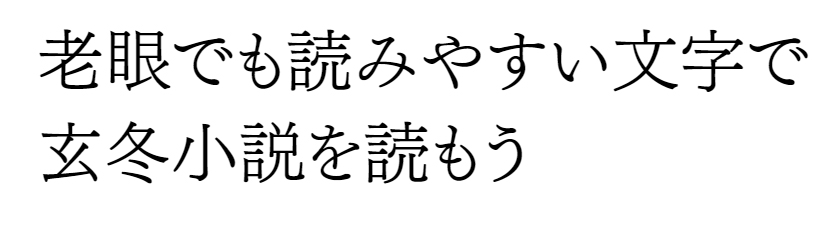
上記の書体はフォントワークスのUD明朝。
本文用書体として高い評価を得ている「筑紫明朝」をベースに、横画を太くし、英数字を大きく調整しました。 読み心地の良さを追求する長文に最適な書体。
若竹千佐子氏・高齢化社会を生きる玄冬小説「おらおらでひとりいぐも」
疎遠になった息子と娘、夫に先立たれ、74歳でひとり暮らしの桃子さんを主人公とした玄冬小説。
玄冬小説って何だろうと思ったら青春小説の対局に位置する小説を意味し、歳をとるのも悪くない、と思えるような小説のことらしい。
石井遊佳氏・芥川賞受賞作品「百年泥」
門井慶喜氏・直木賞受賞作品「銀河鉄道の父」